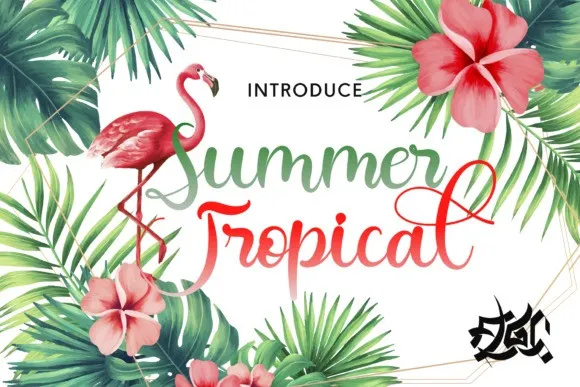
Summer Tropical Font
Esta é uma fonte script moderna que traz variáveis básicas, linhas finas e uma delicada aparência elegante. Ela foi criada pelo designer fontado FallenGraphic Std . Este font proporciona inúmeras escolhas alternativas para caracteres, suportando ligaturas e conjuntos estilizados. É perfeitamente adequada para cartões de convite, mensagens pessoais, materiais de marca, postagem de business card, citações, divulgação social, cartas de casamento e muito mais! Compreender essa fonte traz um toque especial a qualquer projeto que você faça.